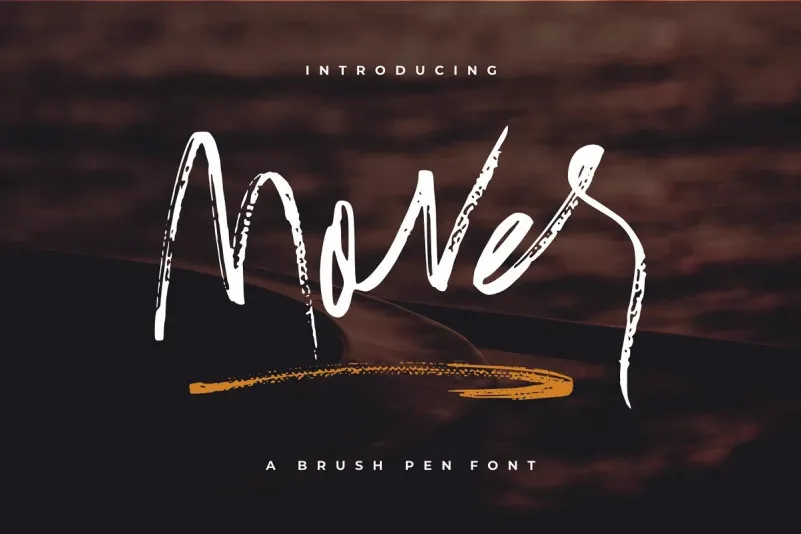
Esta fonte chamada Mover é uma escolha perfeita para projetos criativos, especialmente se você está trabalhando com designs que precisam de um ar natural e moderno ao mesmo tempo. Ela foi desenvolvida pela Floral Studio e possui um detalhamento único da textura de pincel, o que torna a aparência da fonte Kattalyna ainda mais sofisticada e elegante. Seja para criar logos profissionais, anúncios de produtos, títulos de filmes ou capas de livros, a Mover é uma ótima opção. Ela também se destaca na criação de aplicações, com seu estilo único que vai muito além do básico e está sempre em alta demanda entre designers. Não importa o tipo de projeto em que você esteja trabalhando, a Mover definitivamente será um atalho para uma solução elegante e moderna.